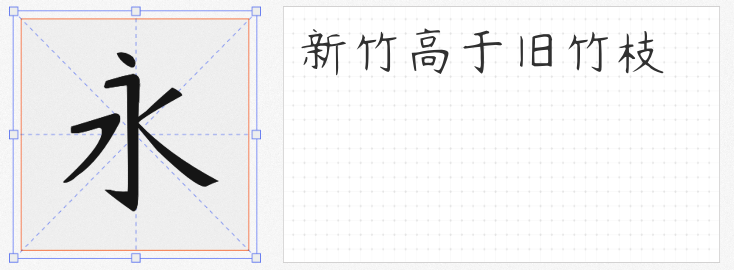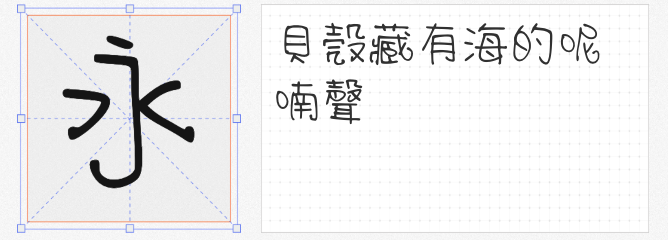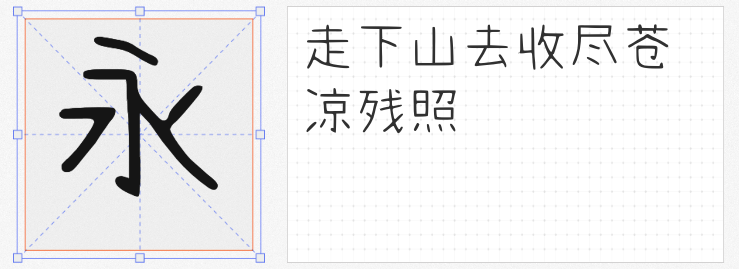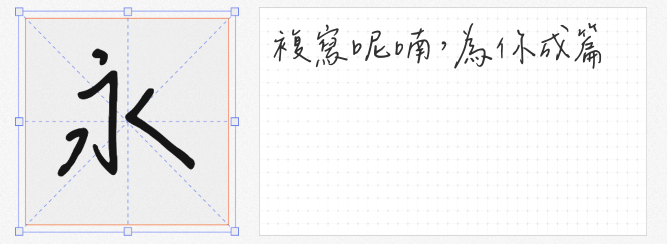
在平面设计中,手写字体以其独特的温度感和艺术性,成为品牌视觉、海报标题、包装设计的点睛之笔。本文精选四款可免费商用的手写字体,涵盖可爱、简洁、水墨感等多元风格,助你轻松提升设计质感。
清松手写体6以圆润饱满的笔画和微微倾斜的字体结构,营造出活泼俏皮的视觉效果。其字形如孩童涂鸦般天真无邪,尤其适合儿童品牌、文创产品或需要传递轻松氛围的设计场景。笔画末端的小弧度设计,让文字在可爱中不失精致感,无论是标题还是短文案都能瞬间抓住眼球。
杨任东竹石体以“竹石”为灵感,将东方书法的飘逸与现代设计的简洁融为一体。Extralight字重版本线条纤细却不失力度,中英文、数字符号全覆盖,适配性强。无论是书籍封面、品牌LOGO还是网页标题,其清雅气质都能为设计注入文化底蕴,尤其适合新中式风格或追求高级感的商业项目。
这款字体通过模拟水笔书写时的“粘连”效果,还原了手写的自然笔触。Thin字重下,笔画粗细变化清晰可见,转折处的墨渍痕迹更添真实感;而粗字重则呈现圆润可爱的视觉效果,适合需要强调亲和力的设计。无论是手账风格插画、咖啡店菜单还是社交媒体图文,都能轻松营造随性而不失精致的氛围。
由韦辰书写、作者后制的辰宇落雁体,以“复写日常”为概念,将手写温度封存于数字字体中。Thin版本线条纤细如羽,笔画间留有呼吸感,仿佛墨迹在纸上自然晕染。其独特的文艺气质,使其成为诗歌集、艺术展览海报或文创品牌包装的理想选择,让设计在商业中保留一份人文情怀。